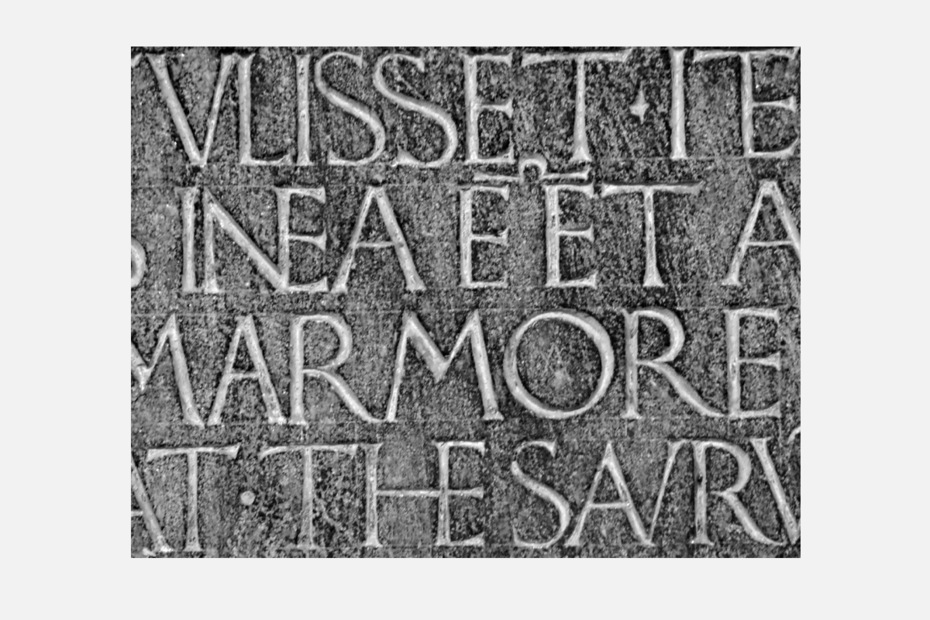
Под­жо Брач­чо­ли­ни и за­га­доч­ная над­пись в Тер­ра­нуо­ва-Брач­чо­ли­ни
е­мо­ри­аль­ная дос­ка с тек­стом Под­жо Брач­чо­ли­ни из цер­кви Свя­той Ма­рии в Тер­ра­нуо­ва-Брач­чо­ли­ни, не­боль­шом то­скан­ском го­род­ке меж­ду Фло­рен­ци­ей и Арец­цо, — од­на из са­мых стран­ных над­пи­сей эпо­хи Воз­ро­жде­ния. Длин­ный текст (18 стро­к) рас­ска­зы­ва­ет, как «один рим­ский гра­жда­нин, бед­ный и ну­жда­ю­щий­ся», се­то­вал Бо­гу на свою жизнь. В че­ре­де снов ему при­ви­дел­ся при­зрак, по­ве­лев­ший раз­ру­шить ал­тарь в цер­кви, по­стро­ен­ной Сик­стом II, ибо под ним скры­ва­лось со­кро­ви­ще. Муж­чи­на сде­лал, как ему бы­ло ве­ле­но, но нашёл лишь «ма­лень­кую мра­мор­ную шка­тул­ку с тре­мя стек­лян­ны­ми со­су­да­ми». Он был ра­зо­ча­ро­ван, но при­зрак ве­лел ему про­дол­жать на­ча­тое, и вско­ре рим­ля­нин нашёл ещё две мра­мор­ные шка­тул­ки, а в од­ной из них об­на­ру­жил стек­лян­ную ва­зоч­ку с чрез­вы­чай­но дра­го­цен­ны­ми ре­лик­ви­я­ми, в том чис­ле ко­стью Ла­врен­тия Рим­ско­го.
Муж­чи­на привёз ре­лик­вии Ри­нуч­чо да Ка­сти­льо­не (Rinuccio da Castiglione), гу­ма­ни­сту и се­кре­та­рю па­пы, и по­про­сил по­мо­щи. Ри­нуч­чо пе­ре­дал ре­лик­вии Под­жо, ко­то­рый, на­гра­див муж­чи­ну, по­ме­стил их в но­вую ча­сов­ню, по­стро­ен­ную в 1438 го­ду в Тер­ра­нуо­ве, его род­ном го­ро­де. Ча­сов­ню уни­что­жи­ли при пе­ре­строй­ке цер­кви в XVII–XVIII ве­ках, со­хра­ни­лись лишь ре­лик­ва­рий Ла­врен­тия Рим­ско­го и ин­те­ре­су­ю­щая нас над­пись. Со­глас­но тек­сту, опи­сы­ва­е­мые со­бы­тия про­ис­хо­ди­ли в 1443 го­ду, над­пись так­же ука­зы­ва­ет, что ре­лик­ва­рий по­ме­сти­ли в ча­сов­ню (по­стро­ен­ную в 1429 го­ду) «anno aetatis mead LVIII», то есть «на 58-й год его жиз­ни». По­сколь­ку Под­жо ро­дил­ся в 1380 го­ду, это со­бы­тие да­ти­ру­ет­ся 1438 го­дом, и пред­по­ла­га­ет­ся, что над­пись бы­ла сде­ла­на то­гда же.
Стран­ность над­пи­си Под­жо за­клю­ча­ет­ся в том, что её бук­вы по­сте­пен­но транс­фор­ми­ру­ют­ся от фло­рен­тий­ско­го гро­те­ска к бук­вам, очень близ­ким по фор­мам к рим­ско­му мо­ну­мен­таль­но­му пись­му. Я не знаю ни од­ной дру­гой над­пи­си пе­ри­о­да Ква­тро­чен­то — а по прав­де ска­зать, и ни­ка­ко­го дру­го­го пе­ри­о­да, — в ко­то­рой бук­вы ве­дут се­бя по­доб­ным об­ра­зом. Хо­тя это­го уже до­ста­точ­но для при­сталь­но­го изу­че­ния над­пи­си, не ме­нее ин­три­гу­ю­щи­ми ока­за­лись при­чи­на из­ме­не­ния букв и ав­тор это­го тек­ста.
Б. Л. Ул­л­ман на­звал Под­жо Брач­чо­ли­ни (1380–1459) «со­зда­те­лем» scrittura umanistica, или книж­но­го гу­ма­ни­сти­че­ско­го пись­ма, ок. 1402/1403. Он так­же пред­по­ло­жил, что ма­юс­куль­ные бук­вы из ма­ну­скрип­тов Под­жо сы­гра­ли зна­чи­тель­ную роль в воз­ро­жде­нии рим­ско­го мо­ну­мен­таль­но­го шриф­та (Roman capitals) в эпо­ху Ре­нес­сан­са. Не­смот­ря на то что не су­ще­ству­ет убе­ди­тель­ных до­ка­за­тельств этой те­о­рии, над­пись в Тер­ра­нуо­ва под­твер­жда­ет его идею о не­со­мнен­ной ро­ли Под­жо в воз­вра­ще­нии букв рим­ско­го мо­ну­мен­таль­но­го пись­ма в оби­ход. Бук­вы в ма­ну­скрип­тах, пе­ре­пи­сан­ных Под­жо, ис­пол­не­ны пе­ром, за­сеч­ки в них ед­ва за­мет­ны или со­всем от­сут­ству­ют. А ма­ну­скрип­ты, ско­пи­ро­ван­ные пис­ца­ми по его при­ка­зу, ча­сто со­дер­жат бук­ви­цы, по­хо­жие на над­пи­си на скульп­ту­рах Ги­бер­ти, До­на­тел­ло, Ми­ке­лоц­цо, Лу­ки дел­ла Роб­биа и дру­гих ху­дож­ни­ков 1412–1440-х го­дов.
Де­таль ма­ну­скрип­та Под­жо (Vat. lat. 1849, fol. 182) (1425—1426)•Ис­точ­ник: The Origin and Development of Humanistic Script by B.L. Ullman (Rome: Edizioni di Storia e Letteratura, 1960).
Ги­бер­ти на­зы­вал свои про­пис­ные lettere antiche, но на са­мом де­ле они, как и бук­ви­цы Под­жо, ско­рее от­но­сят­ся к ка­ро­линг­ским и ро­ман­ским про­пис­ным, а не к Древ­не­му Ри­му. В этих бук­вах есть кон­траст тол­стых и тон­ких штри­хов, штри­хи рас­ши­ря­ют­ся на кон­цах, и у них нет за­се­чек. От­сут­ствие за­се­чек поз­во­ли­ло ис­сле­до­ва­те­лю Ни­ко­лет Грей клас­си­фи­ци­ро­вать их как бук­вы фло­рен­тий­ско­го гро­те­ска. По­доб­ные зна­ки сы­гра­ли свою роль и в над­пи­си из Тер­ра­нуо­вы.
Над­пись в Тер­ра­нуо­ве: 59 см в вы­со­ту и 138 см в ши­ри­ну. Текст со­сто­ит из 18 строк с вы­ключ­кой по ле­во­му краю и по­след­ней стро­кой, вы­ров­нен­ной по цен­тру. В за­ви­си­мо­сти от то­го, в ка­кой стро­ке сто­ят бук­вы, они раз­ли­ча­ют­ся по вы­со­те — от 23 до 25 мм. Про­бе­лы меж­ду сло­ва­ми та­кие уз­кие, что по­рой ка­жет­ся, буд­то их по­про­сту нет. В над­пи­си ак­тив­но ис­поль­зу­ют­ся раз­лич­ные сред­не­ве­ко­вые ухищре­ния по эко­но­мии про­стран­ства: ли­га­ту­ры (вклю­чая не­сколь­ко трёх­бук­вен­ных), бук­вы, впи­сан­ные друг в дру­га, на­кла­ды­ва­ю­щи­е­ся друг на дру­га, вы­хо­дя­щие за ли­нию про­пис­ных, аб­бре­ви­а­ту­ры и Ти­ро­нов et (ам­пер­санд) в фор­ме Z. (Ти­ро­но­вы знач­ки — си­сте­ма сте­но­гра­фии, ко­то­рую изоб­рёл Марк Тул­лий Ти­рон, се­кре­тарь Ци­це­ро­на.) На­чи­ная с 10-й стро­ки меж­ду сло­ва­ми (прав­да, не все­ми) воз­ни­ка­ет puncti (точ­ка) осо­бен­ность, ча­сто встре­ча­ю­ща­я­ся в ан­тич­ных над­пи­сях. В 10-й и 11-й строч­ках эти точ­ки ром­бо­вид­ной фор­мы, но с 12-й они ста­но­вят­ся круг­лы­ми. Свер­ху и сни­зу букв вид­ны свет­лые на­прав­ля­ю­щие ли­нии (на­при­мер, 11-я стро­ка). Воз­ни­ка­ет ощу­ще­ние, что над­пись пы­та­ет­ся вер­нуть­ся из сред­не­ве­ко­во­го ми­ра обрат­но в ан­тич­ный. Это чув­ству­ет­ся и в фор­мах зна­ков.
Если срав­ни­ть ан­тич­ные рим­ские над­пи­си, вы­ре­зан­ные на кам­не рим­ским мо­ну­мен­таль­ным пись­мом, и над­пи­си эпо­хи Воз­ро­жде­ния, вы­ре­зан­ные фло­рен­тий­ским гро­те­ском, в пер­вую оче­редь в них от­ли­ча­ют­ся шесть букв: E, G, M, N, Q и R. В этой ста­тье, го­во­ря о рим­ском мо­ну­мен­таль­ном пись­ме, я ссы­ла­юсь на над­пи­си Тра­я­но­вой ко­лон­ны и по­доб­ные им, а при­ме­ром фло­рен­тий­ско­го гро­те­ска бе­ру над­пись на кан­то­рии Лу­ки дел­ла Роб­биа.
В пер­вой строч­ке над­пи­си из Тер­ра­нуо­вы встре­ча­ют­ся фло­рен­тий­ские М и R, рим­ско-мо­ну­мен­таль­ные E, G и Q и бук­ва N с не­опре­де­лив­шей­ся фор­мой. В бук­ве М край­ние штри­хи па­рал­лель­ны, вер­текс ко­рот­кий, на­вер­шия плос­кие, а рас­пре­де­ле­ние тол­щин ме­ня­ет­ся от стро­ки к стро­ке. У R изо­гну­та но­га. По­доб­ные фор­мы этих зна­ков мы ви­дим и на кан­то­рии Лу­ки дел­ла Роб­биа (1431–1437). До­пол­ни­тель­ные штри­хи в бук­ве Е рас­ши­ря­ют­ся к кон­цу или за­кан­чи­ва­ют­ся за­сеч­ка­ми; у вер­ти­каль­но­го штри­ха в бук­ве G есть за­сеч­ки, а у Q — длин­ный изо­гну­тый хвост. В бук­ве N все три штри­ха оди­на­ко­вой тол­щи­ны и плос­кое на­вер­шие. По хо­ду над­пи­си двой­ствен­ность букв (сме­ше­ние форм рим­ско­го мо­ну­мен­таль­но­го и фло­рен­тий­ско­го гро­те­ска) лишь воз­рас­та­ет, N и R пол­но­стью транс­фор­ми­ру­ют­ся в фор­мы рим­ско­го мо­ну­мен­таль­но­го пись­ма, М ме­ня­ет­ся лишь ча­стич­но, а Е (и род­ствен­ные ей F, L и T) ме­чет­ся меж­ду фор­ма­ми фло­рен­тий­ско­го гро­те­ска и рим­ско­го мо­ну­мен­таль­но­го и, лишь в кон­це опре­де­лив­шись, оста­нав­ли­ва­ет­ся на по­след­нем. G и Q на про­тя­же­нии всей над­пи­си оста­ют­ся вер­ны рим­ско-мо­ну­мен­таль­ным фор­мам. К по­след­ней строч­ке лишь в бук­ве М за­мет­ны фор­мы фло­рен­тий­ско­го гро­те­ска, её край­ние штри­хи уже не па­рал­лель­ны, но вер­текс так и остал­ся ко­рот­ким.
Над­пись из Тер­ра­нуо­вы (осо­бен­но с 12 по 18 строч­ки) мож­но на­звать пер­вым при­ме­ром воз­ро­жде­ния букв Рим­ско­го мо­ну­мен­таль­но­го пись­ма в эпо­ху Ре­нес­сан­са.
Не­смот­ря на то, что над­пись Под­жо в Тер­ра­нуо­ва весь­ма не­обыч­на, это не ано­ма­лия. Уди­ви­тель­но, но она очень по­хо­жа на над­пись на па­мят­ни­ке Кар­ло Мар­суп­пи­ни в Сан­та-Кро­че (см. ил­лю­стра­цию ни­же). Все бук­вы на па­мят­ни­ке Мар­суп­пи­ни, за ис­клю­че­ни­ем бук­вы К, по сво­им про­пор­ци­ям и клю­че­вым осо­бен­но­стям очень по­хо­жи на «фи­наль­ные» ва­ри­ан­ты зна­ков над­пи­си из Тер­ра­нуо­вы. На­вер­шие бук­вы А сна­ча­ла плос­кое (стро­ки 1–3), по­сте­пен­но за­остря­ет­ся (стро­ки 4–6); бук­ва Е уз­кая, и её штри­хи за­кан­чи­ва­ют­ся за­сеч­ка­ми с плав­ным, скруг­лён­ным со­еди­не­ни­ем; в бук­ве G есть сви­са­ние; у М ко­рот­кий вер­текс и не­па­рал­лель­ные край­ние штри­хи; N как с Тра­я­но­вой ко­лон­ны; у Q длин­ный, изо­гну­тый хвост; у R чуть изо­гну­тая диа­го­наль­ная но­га; бук­ве S слож­но сто­ять пря­мо; круг­лые точ­ки ис­поль­зо­ва­ны как puncti (но толь­ко на кон­цах строк). Тут так­же при­сут­ству­ет Ти­ро­но­ва et, хо­тя и в сво­ей стан­дарт­ной 7-вид­ной фор­ме. Прин­ци­пи­аль­ные от­ли­чия над­пи­си Мар­суп­пи­ни от над­пи­си Под­жо — в за­сеч­ках (а точ­нее, в их по­сто­ян­стве), вы­со­ком ка­че­стве резь­бы и ком­по­зи­ции с бóль­шим ко­ли­че­ством воз­ду­ха вну­три (че­му так­же спо­соб­ству­ет и дли­на тек­ста, все­го 6 строк).
Millard Meiss, «Towards a More Comprehensive Renaissance Paleography» in The Art Bulletin, том 42, н. 2 (June 1960), с. 98–99
Millard Meiss, Towards a More Comprehensive Renaissance Paleography in The Art Bulletin, том 42, н. 2 (June 1960), с. 98–99.
Толь­ко бук­вы К и М на па­мят­ни­ке Мар­суп­пи­ни силь­но от­ли­ча­ют­ся от их ан­тич­но­го ва­ри­ан­та. Все бук­вы (за ис­клю­че­ни­ем К, в ко­то­рой вид­ны её гре­че­ские кор­ни, и Ти­рон­ской et) вы­гля­дят близ­ки­ми род­ствен­ни­ка­ми над­пи­си из Тер­ра­нуо­ва. — Прим. ав­то­ра